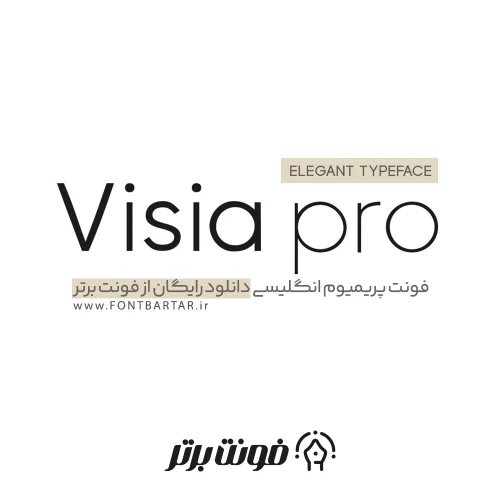
فونت پریمیوم VISIA Pro
فونت پریمیوم VISIA Pro حروف برجسته هندسی Sans-Serif ، ترکیبی عالی از زیبایی شناسی طراحی ظریف، مینیمال و ممتاز در بهترین سطح فونت انگلیسی. بهترین فونت انگلیسی عالی برای لوگوتایپ ها، عنوان ها، برندسازی، طراحی لوگو، هویت های بصری و . . .
بهترین فونت انگلیسی برای تایپ VISIA دارای 7 وزنه است (و همچنین نسخه ایتالیک هر وزن): بسیار سبک / سبک / معمولی / نیمه پررنگ / بسیار پررنگ / سنگین. این بسته حاوی OTF، TTF و فونت های وب (همه EOT، SVG، TTF، WOFF است).